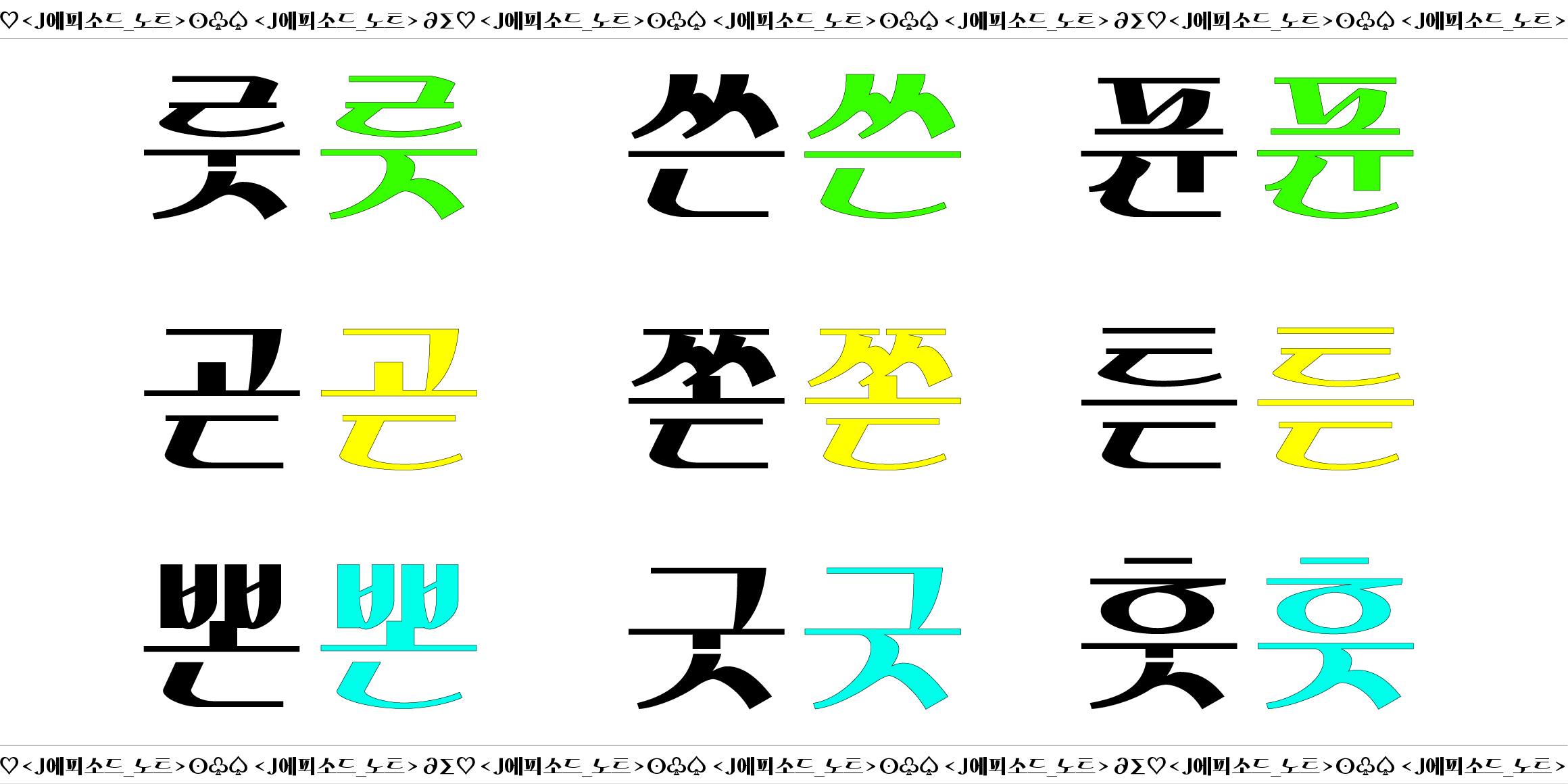
J에피소드_노트
직지소프트의 에피소드_노트는 J에피소드 패밀리의 세번째 시리즈입니다. 2020년 J에피소드, 2021년 J에피소드_플래시백 그리고 2022년에 J에피소드_노트 순으로 출시되었습니다.
에피소드_노트는 패밀리의 “획 대비” 와 “그래픽체” 안에서 손글씨의 필기감의 디테일을 살린 서체로 패밀리로서의 통일감을 주기 위해 네모 고딕의 골격을 유지하되, 납작 펜으로 직접 써가며 필기 시에 표현할 수 있는 디테일을 더했습니다. 01, 02, 03으로 총 3종의 웨이트로 구성되어 있으며, 01은 획대비를 없앤 것이 특징입니다. 세로모임 글꼴 종성 ㄴ 계열 80개, 종성 ㄷ 계열 28개, 종성 ㅅ 계열 18개의 추가 글립을 제공합니다.